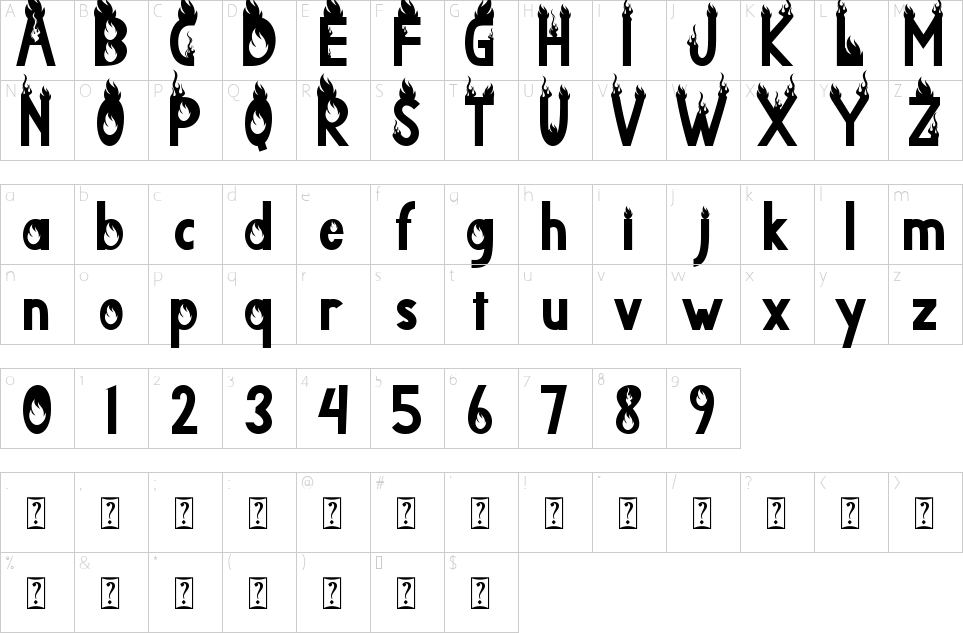
Descubra a fantasia do Ghost Blaze Font para seu próximo projeto. Inspirado no brilho poderoso das chamas mortais, esta elegante fonte oferece uma escolha única e vibrante para gráficos digitais. Desenvolvida por Yoga Letter, o Ghost Blaze vem com um estilo agressivo que pode transformar textos de forma impactante em designs de logotipo ou qualquer projeto visual. Com seu design cuidadosamente elaborado, a fonte tem sido amplamente utilizada e descarregada mais de 3900 vezes. Se você está procurando por uma opção única para dar vida aos seus projetos digitais, o Ghost Blaze pode ser a escolha perfeita.